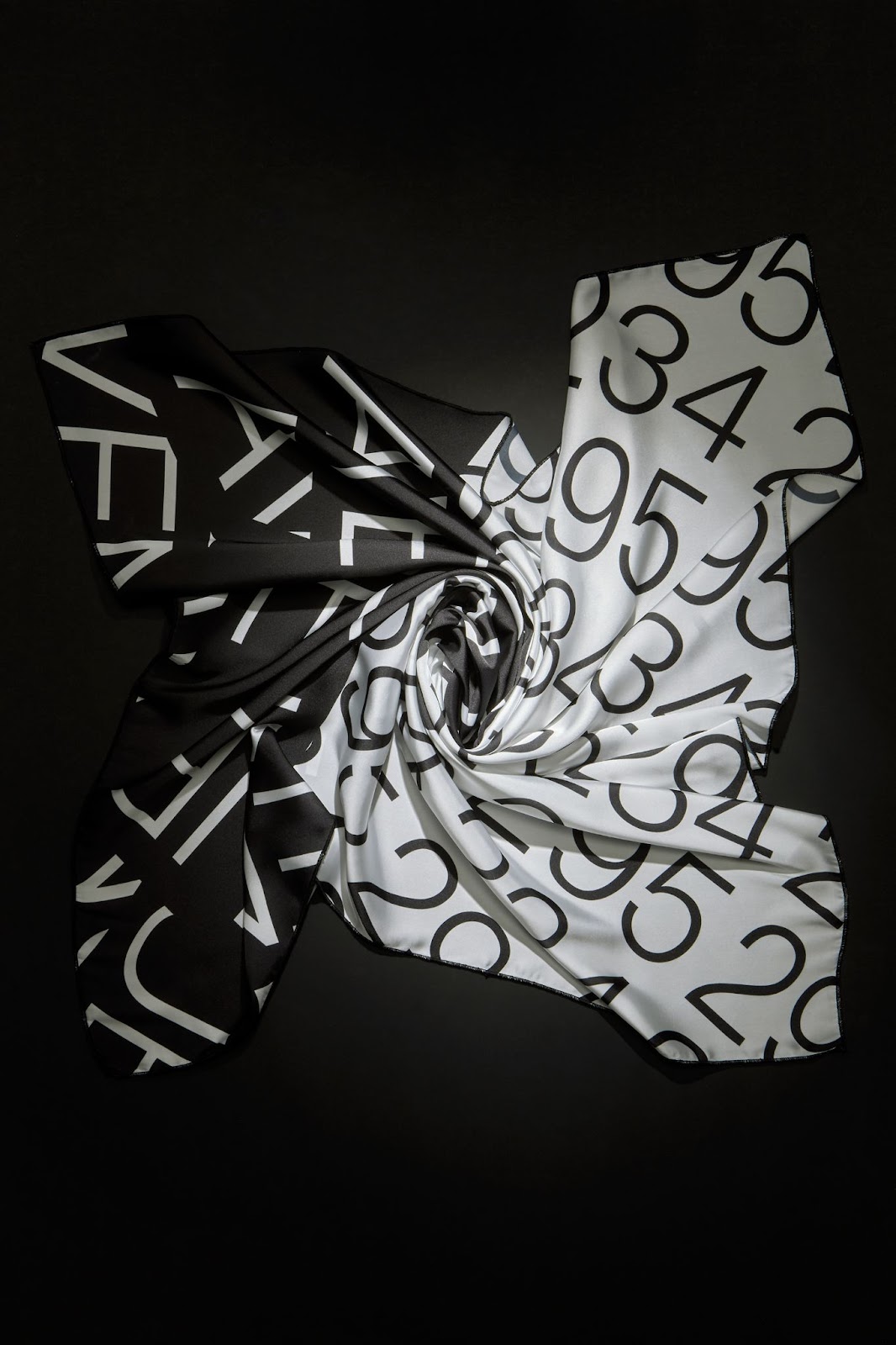
Tipografía experimental y movimiento en bufandas.
Descubra cómo Alexandros Katakalos utilizó tipografía experimental y bufandas para dibujar el movimiento humano y caminos abstractos en esta característica de diseño única.
Alexandros Katakalos explora la intersección del movimiento y el diseño textil en el proyecto Typographic Paths. Este trabajo utiliza tipografía experimental para crear un mapa visual del viaje humano. Este proyecto se centra en el concepto de caminos. Utiliza distorsión tipográfica para mostrar conexiones y direcciones. Cada bufanda es un lienzo para esta exploración.
El proceso de diseño implica estirar y torcer el texto. Catakalos utiliza formas tipográficas y números superpuestos. Fragmentos de texto chocan sobre la tela. Estos elementos se fusionan en composiciones abstractas. Estos diseños reflejan la complejidad de las rutas físicas y espirituales. Este enfoque convierte letras estáticas en instantáneas dinámicas de movimiento. Las letras retorcidas crean un nuevo lenguaje visual. Los cambios en las coordenadas reflejan la imprevisibilidad de los viajes humanos.
La bufanda representa una mezcla de diseño gráfico y textiles. En esta obra, la tipografía no se comunica a través del texto tradicional. En cambio, utiliza el ritmo y la tensión para contar la historia. El flujo del diseño imita el caos del movimiento del mundo real. Catakalos ve la tela como un mapa en constante evolución. Cada pliegue de la seda cambia la perspectiva de la fuente. Esta interacción hace que el diseño cobre vida.
El proyecto destaca cómo la tipografía puede funcionar como herramienta abstracta. Se pasa de la legibilidad a la emoción. La atención se centra en el acto de exploración en sí. Al utilizar seda, el diseñador añadió una capa táctil a la obra impresa. La elección de materiales complementa la fluidez de los gráficos. El resultado es una serie de obras estructuradas y espontáneas.
Esta colección desafía el uso estándar de fuentes en branding o UI/UX. Requiere que el espectador vea primero las letras como formas. Las capas de la obra sugieren profundidad. Representa los muchos caminos que tomamos en la vida. Katakalos cierra la brecha entre el mundo digital y los objetos físicos. Este proyecto es un estudio del flujo visual y las relaciones interpersonales. Capta la esencia del movimiento de forma permanente. La pieza final se convierte en una obra de arte portátil que documenta el viaje.